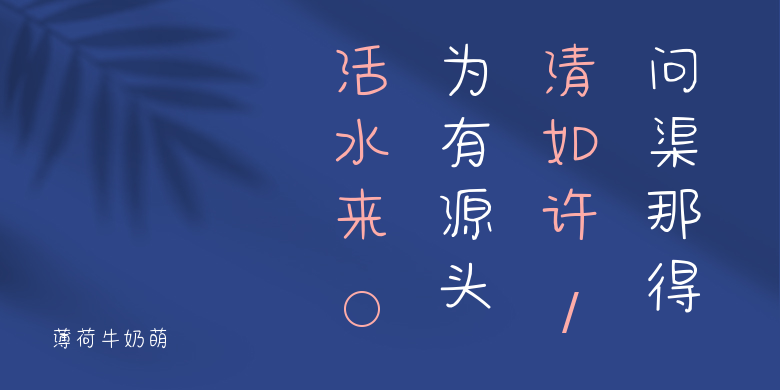
薄荷牛奶萌
薄荷牛奶萌,这款字体结构工整、笔画清晰,兼顾美观与易读性,适用于标题、正文、海报、包装、LOGO 等多种场景。字形优雅稳定,风格百搭耐看,适配日常排版与创意设计,让文字呈现更舒适、更具质感。薄荷牛奶萌一笔一画,皆是细节,以均衡的比例、流畅的线条打造舒适视觉体验,字形端正大气,风格简约现代。无论是商业设计、品牌宣传还是日常排版,都能轻松驾驭,让文字更有格调与力量。薄荷牛奶萌字体下载。